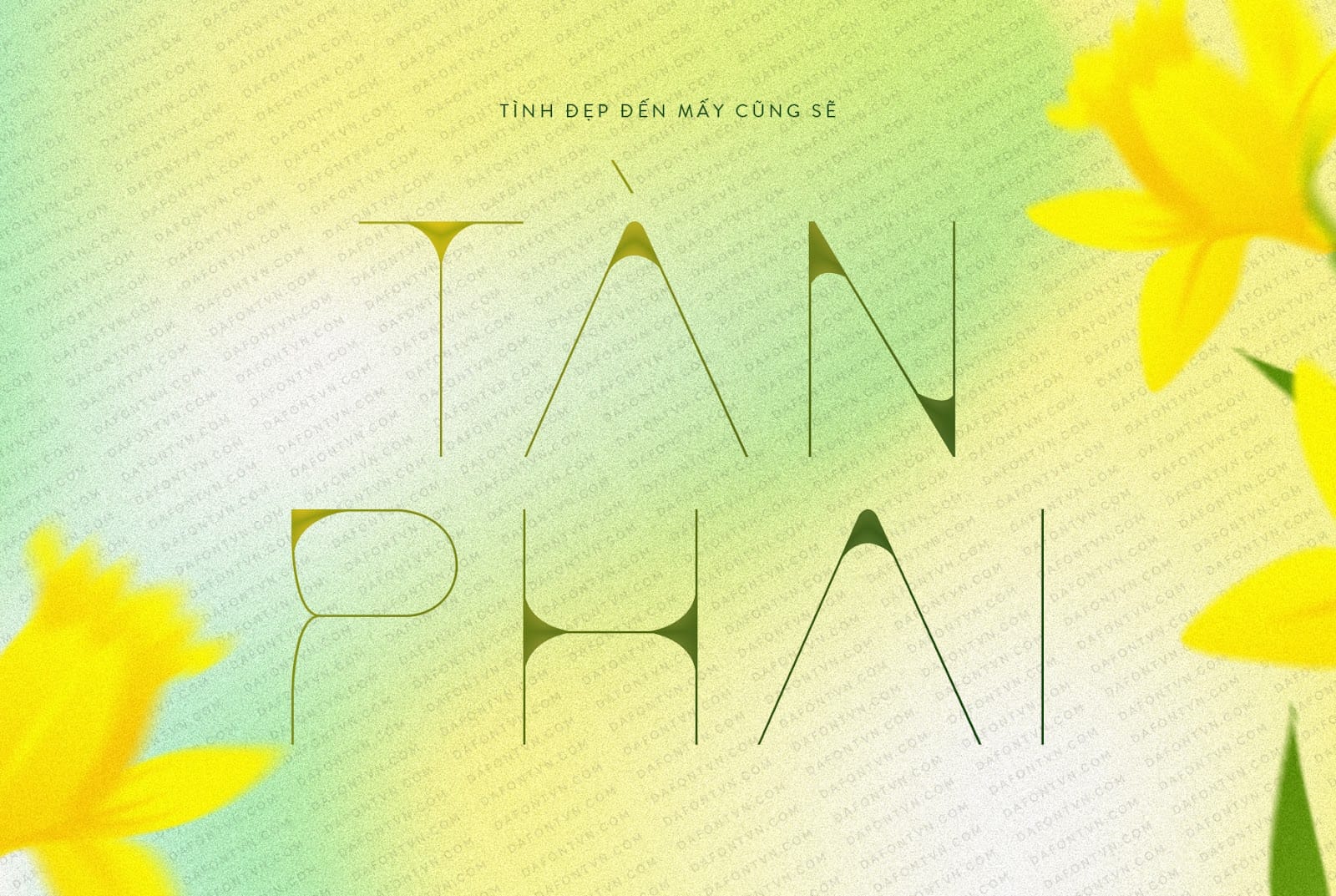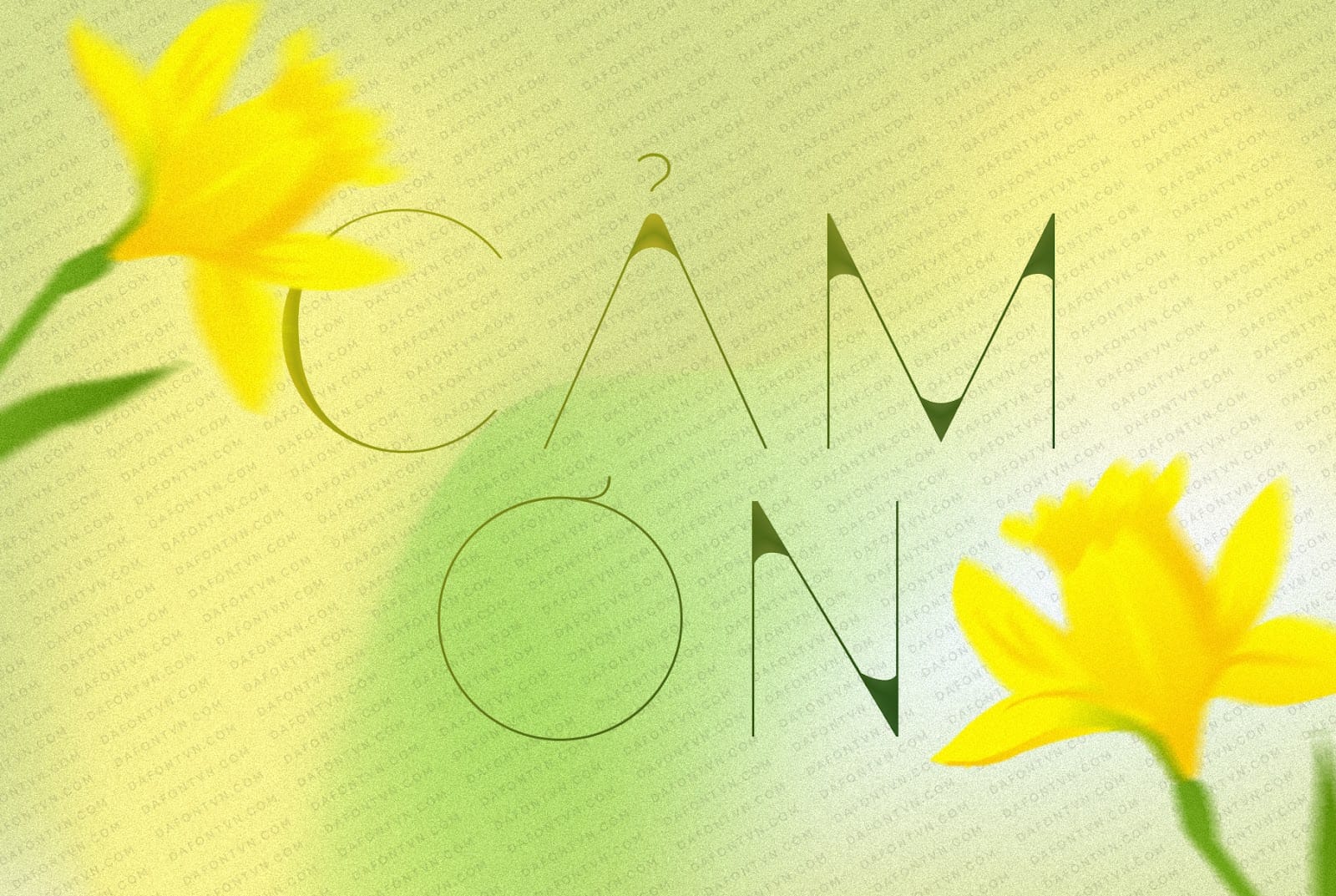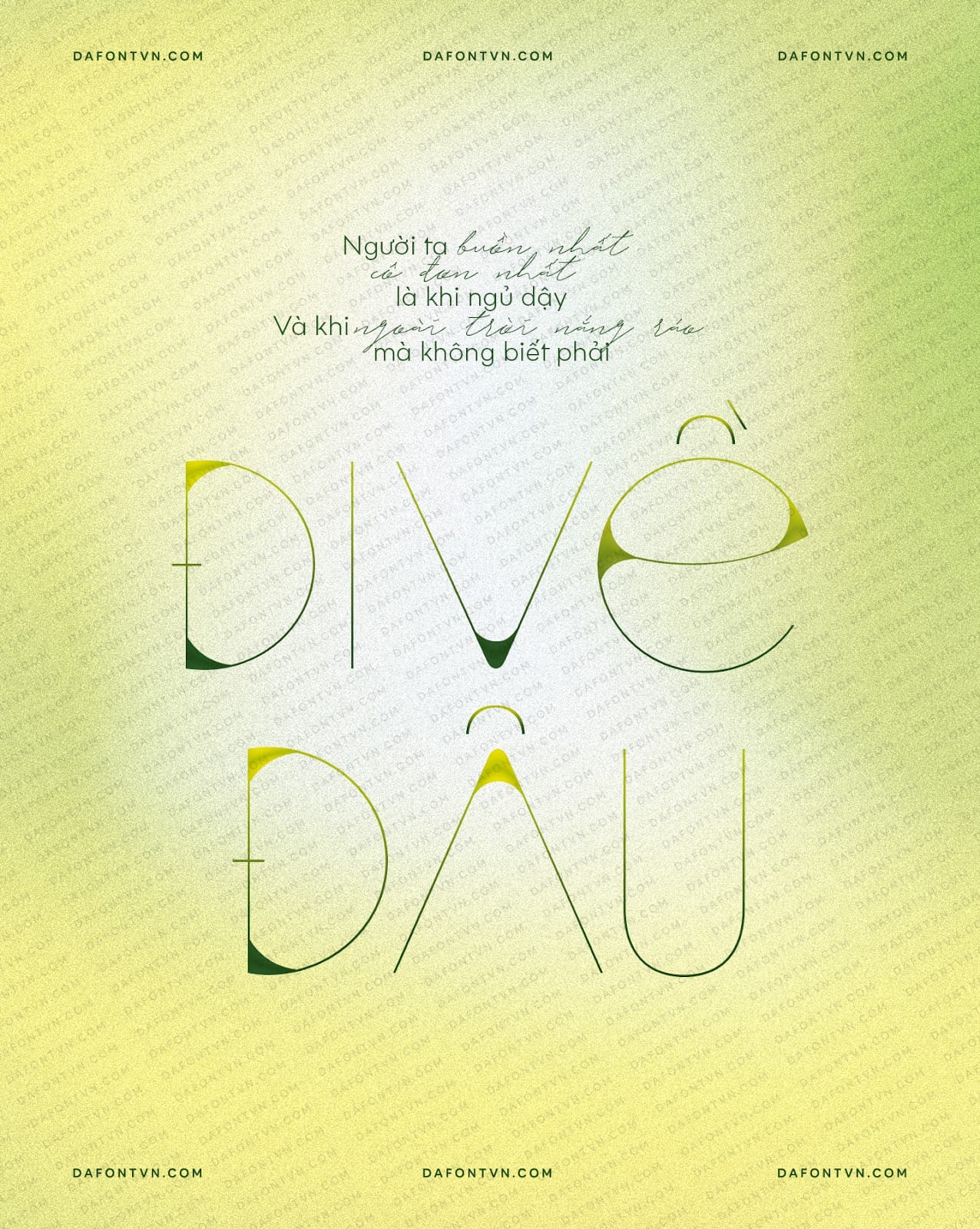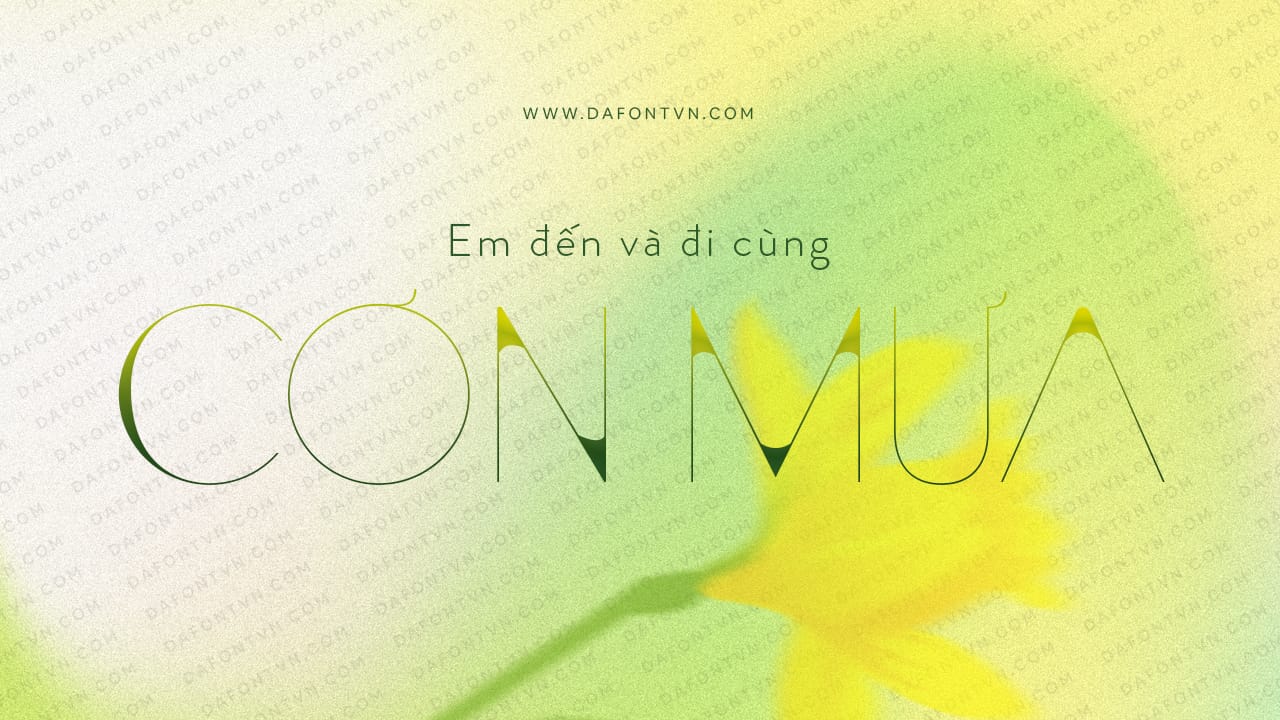
Saneyi là một font chữ hiển thị vui nhộn, phong phú và giàu cảm xúc. Phông chữ này hoàn hảo cho rất nhiều thiết kế khác nhau như tiêu đề, logo, tạp chí, sinh nhật, thiệp mời, lễ kỷ niệm…
Các nét chữ được thiết kế thanh mảnh ấn tượng và điểm nhấn ở các cạnh với các nét đậm mang đến cho bạn một kiểu chữ đẹp mắt và chắc chắn Saneyi sẽ “thổi hồn” vào các ý tưởng sáng tạo của bạn để có những tác phẩm nổi bật.